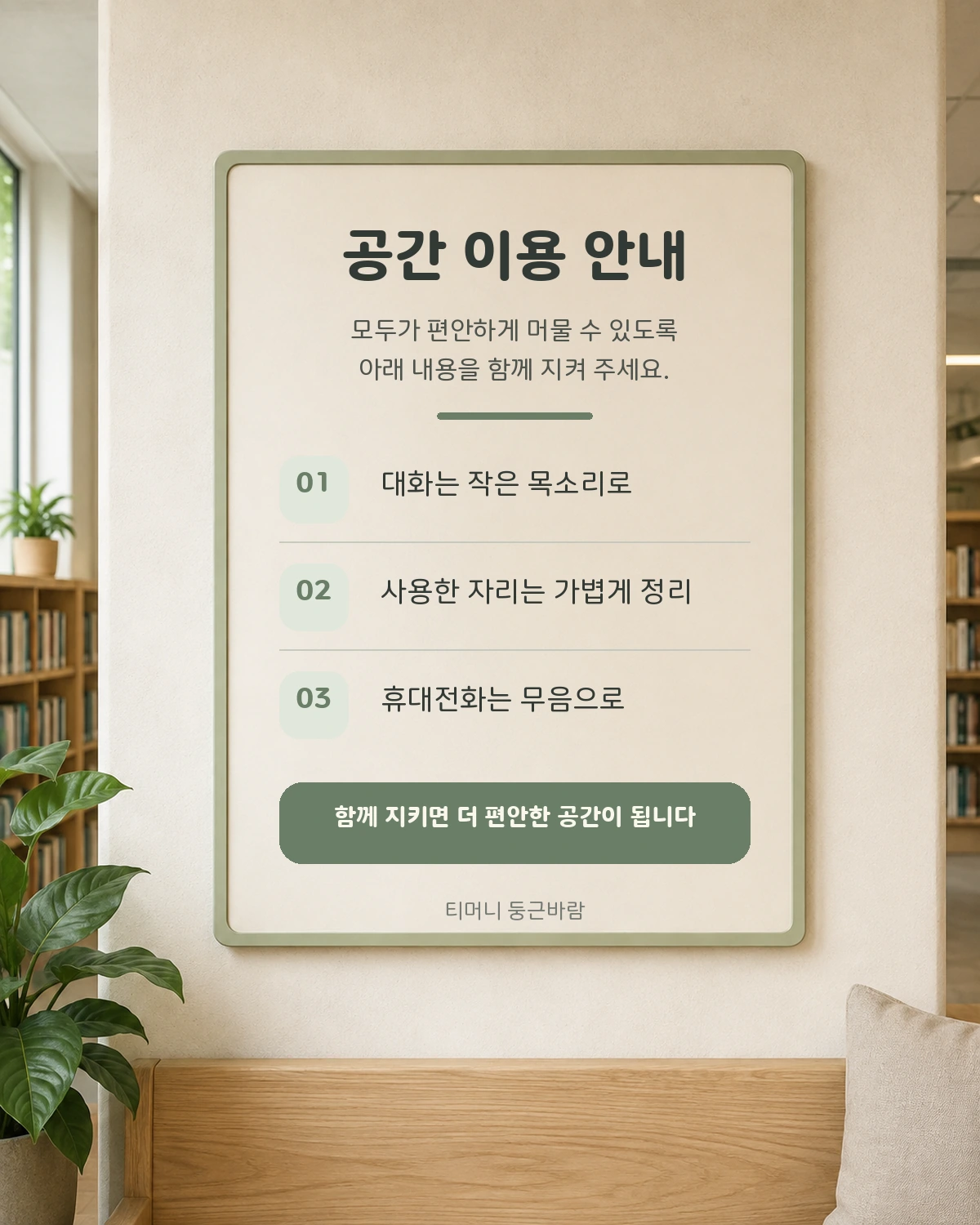
티머니 둥근바람 — 티머니X윤디자인에서 배포하는 무료 폰트입니다. 스마트한 이동과 결제라는 미션에서 출발해 둥글게 굴린 획을 쓴 모빌리티 브랜드 고딕체
티머니가 2019년 연말에 공개한 전용 서체로 윤디자인이 제작했습니다. 회사의 미션인 스마트한 이동과 결제 서비스로 더 편리한 세상을 만든다는 문장에서 출발해, Smart와 Mobile을 디자인 콘셉트로 삼았다고 밝히고 있습니다.
조형에서 눈에 띄는 것은 실용적인 판단입니다. 대문자 I와 소문자 i처럼 헷갈리기 쉬운 글자들은 형태에 차이를 두어 구별되게 했고, 소문자 a와 구두점은 유연하고 단순한 형태로 정리해 통일감을 냈습니다. 교통카드와 단말기 화면처럼 짧은 정보를 정확히 읽어야 하는 환경을 염두에 둔 조정으로 보입니다.